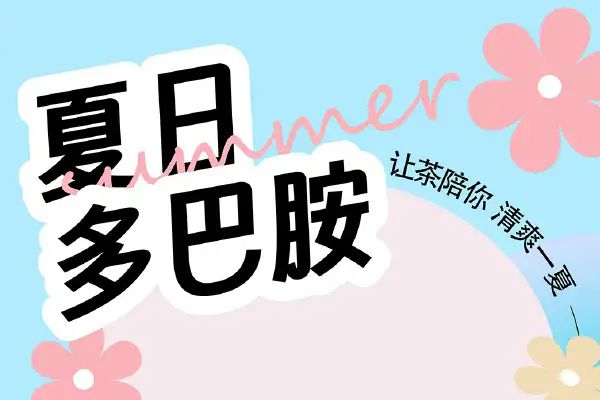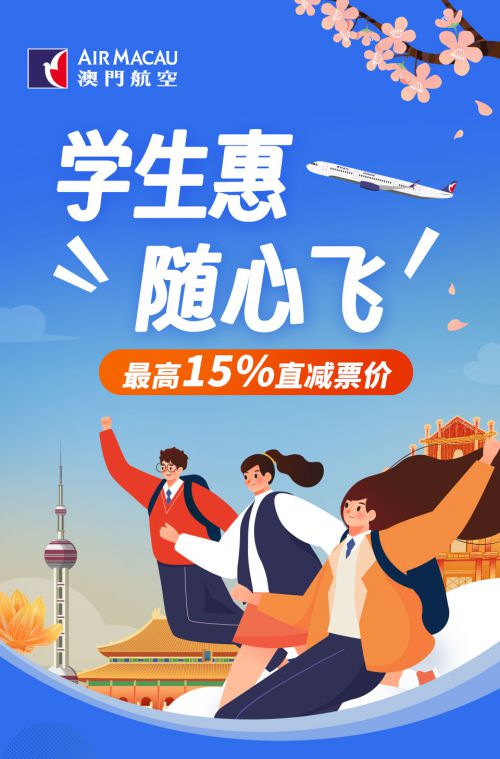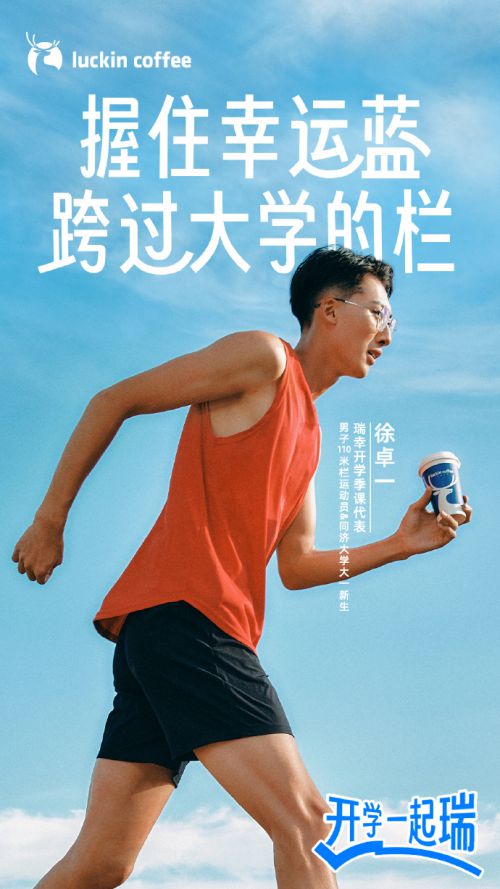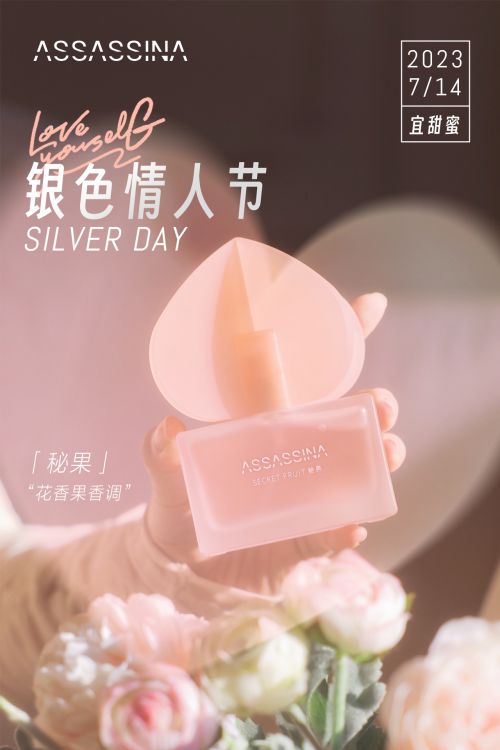
得意黑
得意黑是一款由设计师@oooooohmygosh与@atelierAnchor锚坞联合打造的创意字体,以“有趣”为核心风格,因独特的弯钩造型得名。作为免费商用且开源的字体,得意黑打破传统设计边界,支持用户参与共创,既保留了实用价值,又注入了互动趣味,成为创意设计领域的亮眼选择。 得意黑字形结构方正稳重,字体重心居中,中宫适中的比例让整体视觉平衡且舒展。笔型采用利落直角设计,搭配粗体字重与均匀的笔画粗细,赋予字体鲜明的力量感;方头笔画与局部断开的连接方式,则为方正结构注入灵动细节——棱角分明的线条与刻意留白的笔画间隙,既强化了几何美感,又避免了视觉呆板,无论是标题设计、品牌LOGO还是创意海报,都能凭借独特的“方中带巧”气质快速抓住眼球。